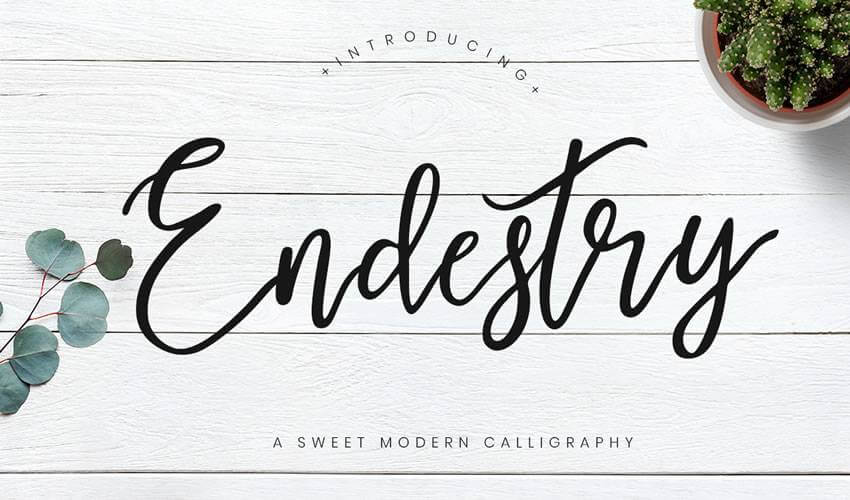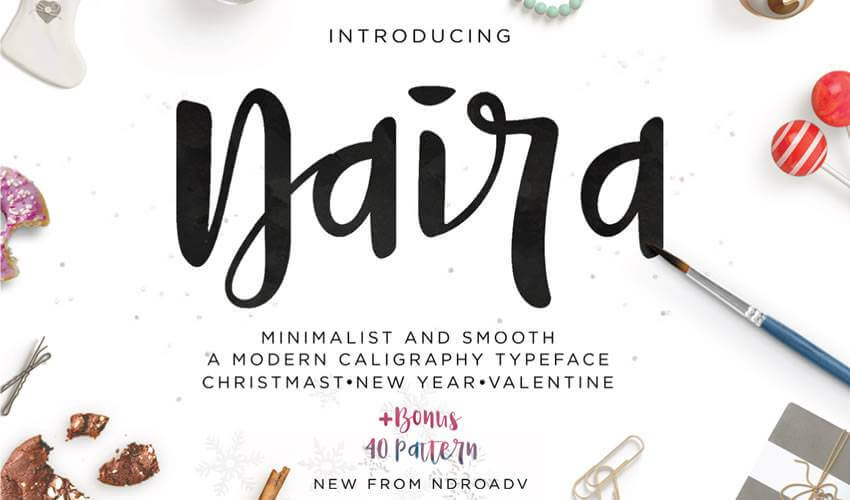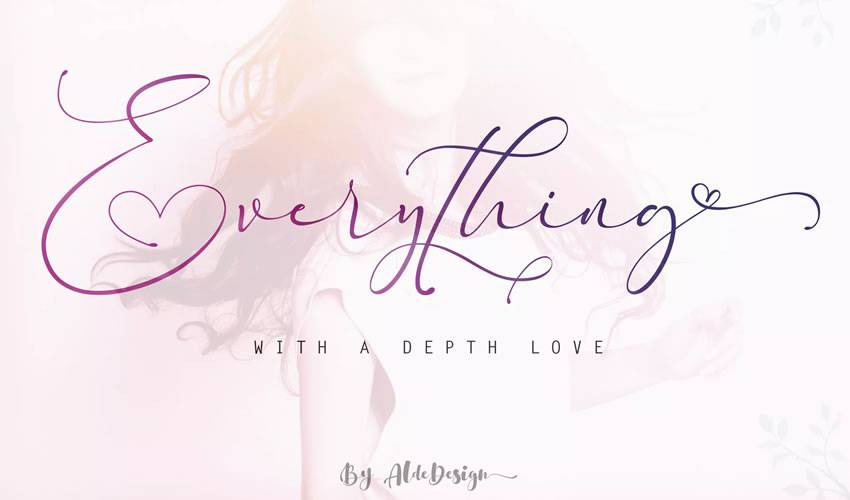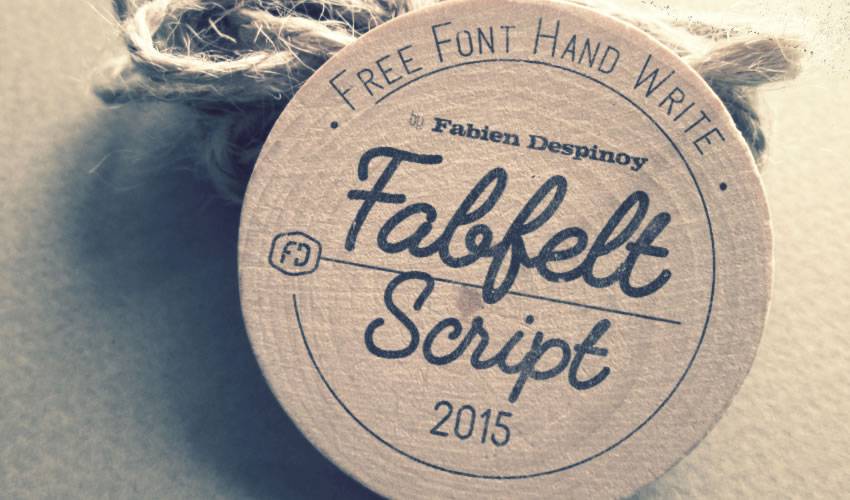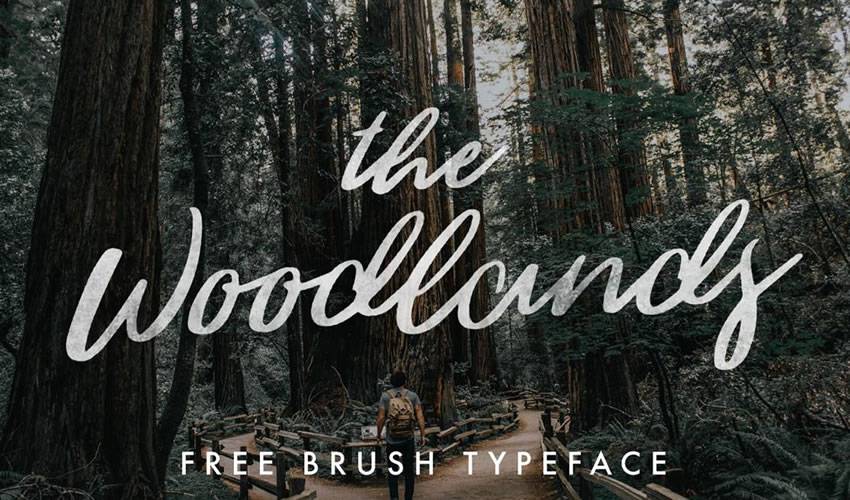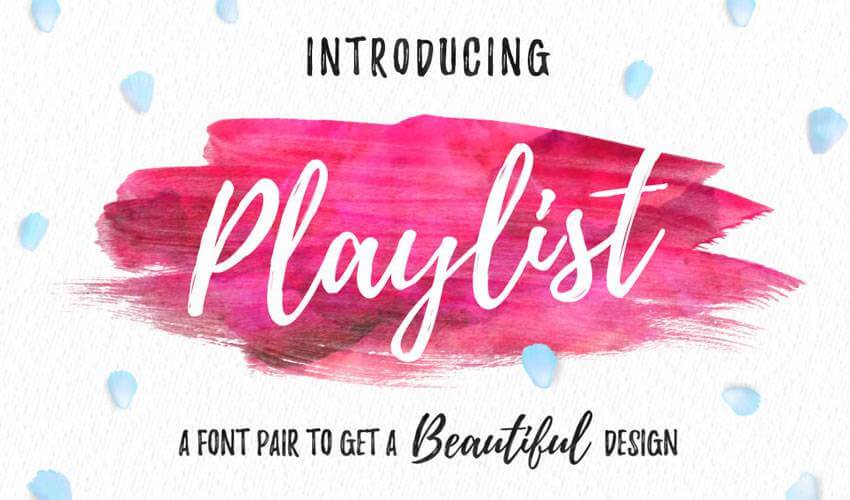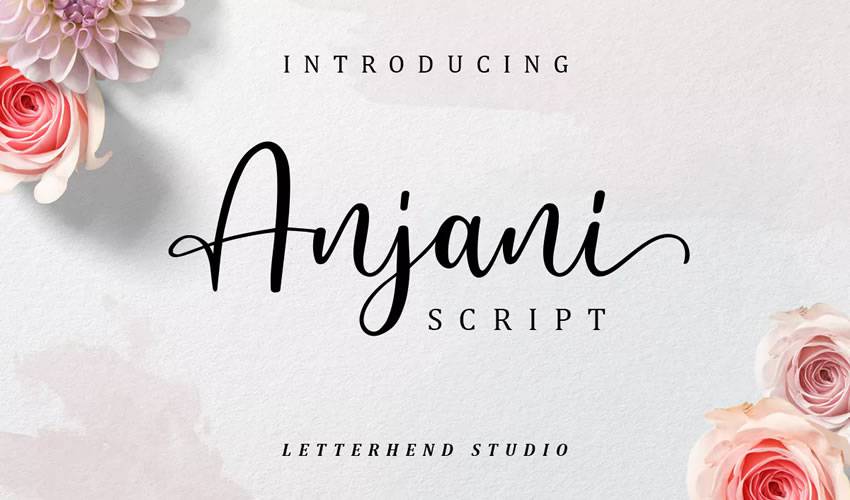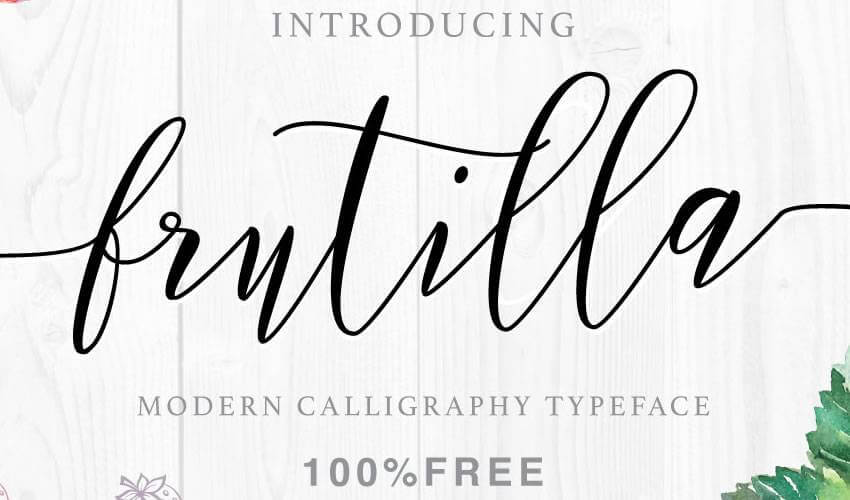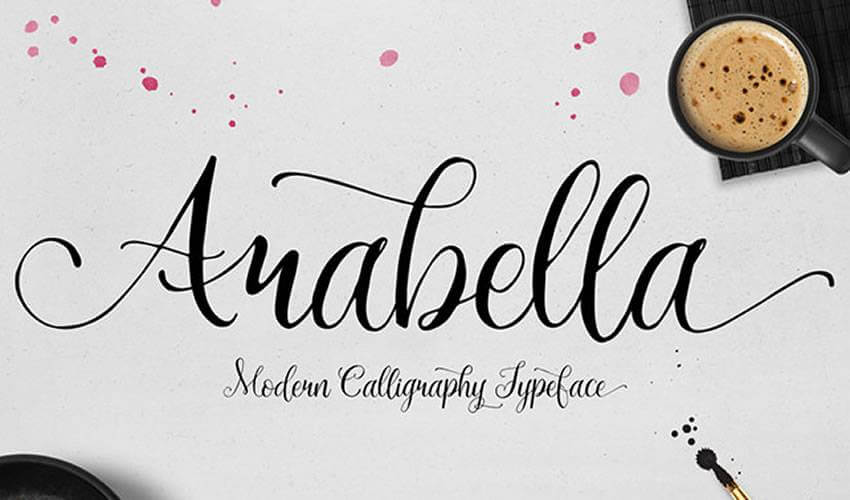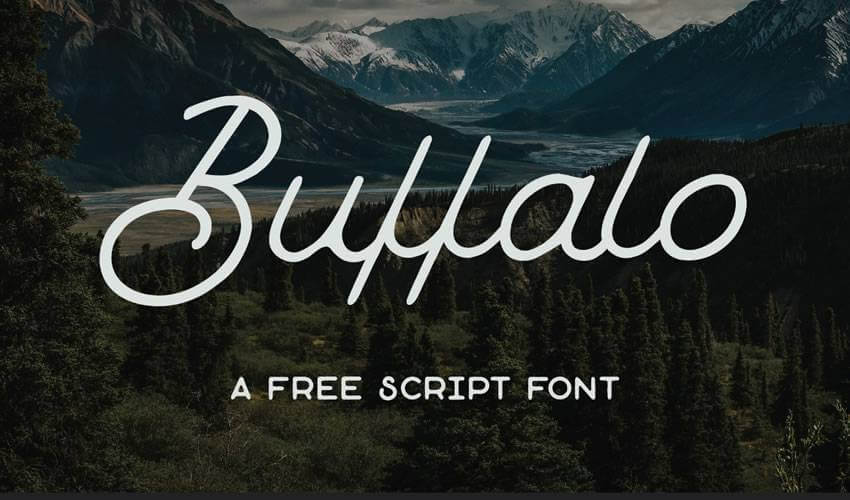
使ってみよう! エレガントなカリグラフィーのフォント24選
デザイナーのツールボックスには、いくらフォントがあっても足りませんが、特に、今人気のカリグラフィーフォントは欠かせないでしょう。カリグラフィーフォントは、どんなデザインプロジェクトにもエレガントなタッチを加えてくれますし、もちろん個性や特徴を表現するのにも最適です。
さらに、カリグラフィーフォントは、ロゴやブランディング、招待状やポスターなど、さまざまなプロジェクトで使用することができます。
お役立ち情報として、業務用、個人用を問わず、高品質な無料のカリグラフィーフォントがオンラインで数多く提供されていることをご紹介しましょう。以下に挙げる最高のカリグラフィーフォントをご覧ください。
Endestry Modern Calligraphy Font (Free)
CreatypeスタジオがデザインしたEndestryは、素晴らしい流れを特徴としています。ロゴやブランディングだけでなく、レターヘッドや招待状、ソーシャルメディアへの投稿などにも最適なフォントとなっています。
Billowing Script (Envato Elements)
Billowing Scriptは、自然からインスピレーションを受けたモダンなカリグラフィーフォントです。243のグリフと64の代替文字に加え、様式的代替、標準合字、その他のOpenType機能を備えています。
Naira Script (Free)
Naira Scriptは、太めのストロークと多くの代替文字や合字を備えた無料のカリグラフィーフォントで、あなたのデザインに個性を加えることができます。アーティストのブランディングや、ソーシャルメディアでの投稿を目立たせたい場合に最適です。
Everything Calligraphy (Envato Elements)
Everything Calligraphyは、様々なベースラインが特徴で、あなたのアートに快活さと遊び心を与えます。このフォントは、Envato Elementsのサブスクリプションに無料で含まれており、結婚式の招待状に最適です。
Fabfelt Script Free Font (Free)
ちょっとしたビンテージ感を出したいなら、Fabfelt Scriptを試してみてはいかがでしょうか。Despinoy Fabienがデザインしたこのフォントは、端正な文字が特徴的です。個人用にも業務用にもお使いいただけます。
Anjani Script Modern Calligraphy (Envato Elements)
Anjaniは、Envato Elementsに登録するとダウンロードできるフォントのひとつです。モダンでロマンチックな印象を与えるため、結婚式の招待状、ロゴ、Tシャツのデザイン、レターヘッドなどに適しています。
The Woodlands Font (Free)
Woodlandsは、ややしっかりした印象を与える毛筆風カリグラフィーフォントです。アウトドアや自然をテーマにした商品のブランディングに最適なフォントです。個人用・業務用ともに無料でご利用いただけます。
Mustahe Brush Script (Envato Elements)
これもまた、汎用性の高いフォントを探している方にお勧めです。Mustahe Brush Scriptには、スクリプト、ラウンド、スムースの3つのスタイルが用意されています。これらのスタイルを組み合わせることで、個性的でありながら調和のとれたデザインを実現することができます。
Playlist font (Free)
デザインにちょっとした変化をつけたいなら、Playlistを検討してみてはいかがでしょうか。スクリプト、オーナメント、キャップの3つのスタイルがあり、これらを組み合わせてユニークなデザインを作ることができます。個人用にも業務用にも使用できます。
Love Rosnita Font (Envato Elements)
Rosnitaは、弾むような、流れるような感じのフォントです。このフォントでは、エレガントな筆記体とサンセリフ体が得られます。この2つを組み合わせてデザインすると、マッチしていながらユニークな印象を与えます。これは、署名や強調のフォントとしてだけでなく、Instagramの投稿用の引用フォントとしても使えます。
Frutilla Script (Free)
Frutilla Scriptは、Ianmikraz Studioがデザインした、エレガントでクラシックな外観が特徴の筆記体です。このフォントには250以上のグリフと豊富なOpenType機能が含まれており、装飾文字も含まれているため、汎用性が高くなっています。個人用でも業務用でも無料でご利用いただけます。
Feelsmooth Script (Envato Elements)
Feelsmooth Scriptは、ブランディングやロゴに最適な筆記体です。ベースラインを変化させることで、エレガントで流れるような雰囲気を醸し出しています。350以上のグリフと167の代替文字を備えています。
Arabella Script Font (Free)
Arabella Scriptは、遊び心のあるロマンチックな筆記体のフォントで、個人的なプロジェクトであれば完全に無料で使用することができます。ロゴはもちろん、招待状やTシャツのデザインにも適しています。
Buffalo Font (Free)
Buffaloは、個人用にも業務用にも使用できるフリーの筆記体フォントです。ちょっとしたビンテージ感とエレガントな雰囲気があり、とてもユニークな印象を受けます。ブランディングや看板、販促物などにお使いいただけます。
Hello Stockholm Typeface (Free)
Hello Stockholmは、スカンジナビアのミニマリズムにインスパイアされた、モダンな毛筆風の筆記体フォントです。結婚式の招待状や街頭広告、Instagramの投稿、Tシャツのデザイン、ブランディングなどにお使いいただけます。このフォントには、大文字と小文字の代替文字のほか、多言語に対応したサンセリフ体も含まれています。
Carosello Font (Free)
目立たせたいフォントをお探しの方は、Caroselloをお試しください。レトロな雰囲気を持つこのフォントは、ビンテージ系のプロジェクトに最適です。個人用であれば無料で使用できます。
Aprillia Script (Free)
Aprillia Scriptは、ソーシャルメディアへの投稿やロゴ、Tシャツのデザインなどに最適な、モダンで大胆な筆記体フォントです。個人用には無料でお使いいただけます。
Olivia Script Font (Free)
エレガントで洗練された印象を与えたいのであれば、Olivia Scriptは最適です。このフォントには351のグリフが含まれており、業務用でも個人用でもお使いただけます。
Noelan Font (Free)
Noelanには、単語の最初と最後に自動的に接続されるエレガントな飾りが含まれています。このフォントは、業務用、個人用を問わず無料で使用でき、万国の文字だけでなく、代替文字も多く含まれています。
Alex Brush Font (Free)
Alex Brushの特徴は、ベースラインより下のディセンダー部分が短いことで、他の類似した筆記体フォントよりも読みやすくなっています。業務用、個人用を問わず無料でご利用いただけます。
Salmela Calligraphy Font (Free)
Salmelaは、モダンで大胆な印象を与える美しい毛筆風フォントです。レタリングのプロジェクト、ウォールアート、ポスターなどに最適です。業務用でも個人用でも無料でご利用いただけます。
Allura Font (Free)
一見してAlluraが結婚式の招待状やステーショナリーに最適なフォントであることがわかります。エレガントで上品な外観を特徴としており、業務用にも個人用にもお使いいただけます。
Autery Script Font (Free)
Autery Scriptは遊び心のあるデザインで、若年層向けの製品やブランドを含むブランディングプロジェクトに最適です。業務用、個人用を問わず無料でご利用いただけます。
Easy November Font (Free)
Easy Novemberは、ブランディングプロジェクトやプロモーションキャンペーンに最適なフォントです。エレガントなスタイルの飾りが含まれており、個人用でお使いいただけます。
カリグラフィーフォントは、あなたのデザインにスタイルと個性を与えます。また、ブランディングプロジェクトやTシャツのデザイン、レターヘッド、文房具のデザイン、結婚式の招待状などにも使用できる汎用性の高いフォントです。
上記でご覧いただいたように、個人用にも業務用にも使える高品質なカリグラフィーフォントがたくさんありますので、ぜひチェックしてみてください。